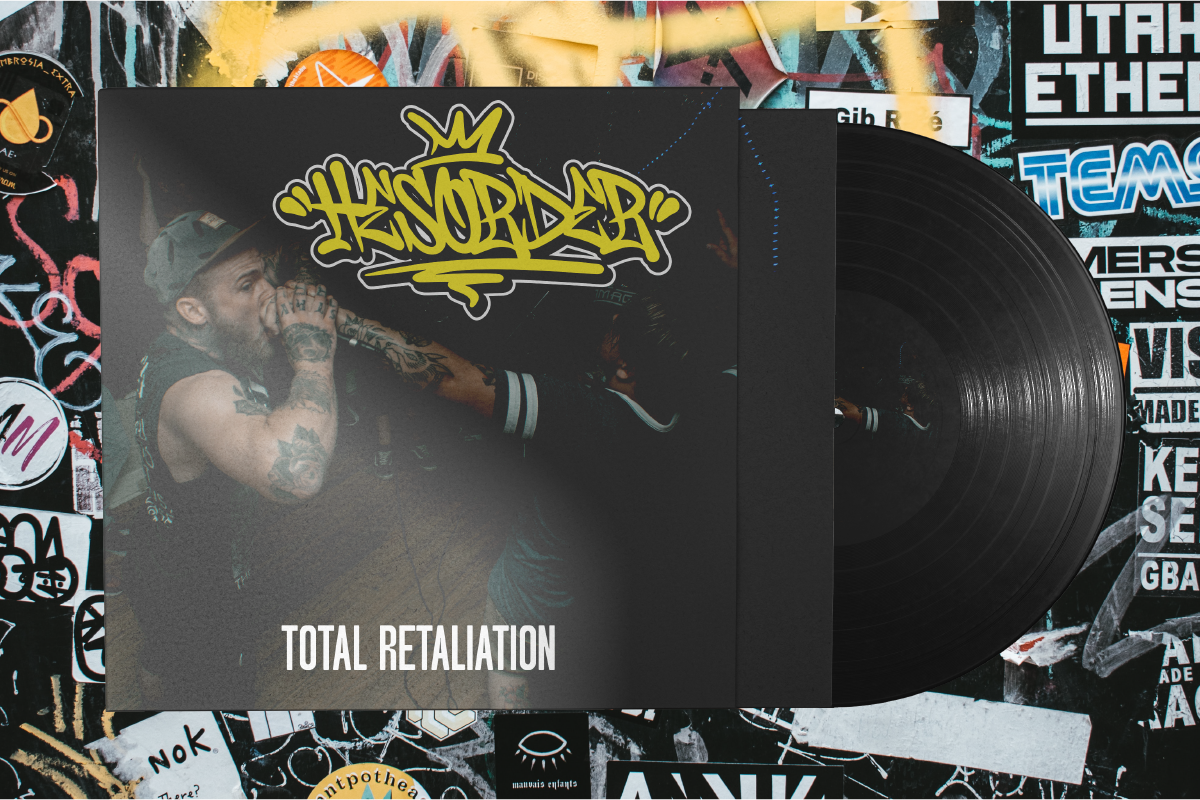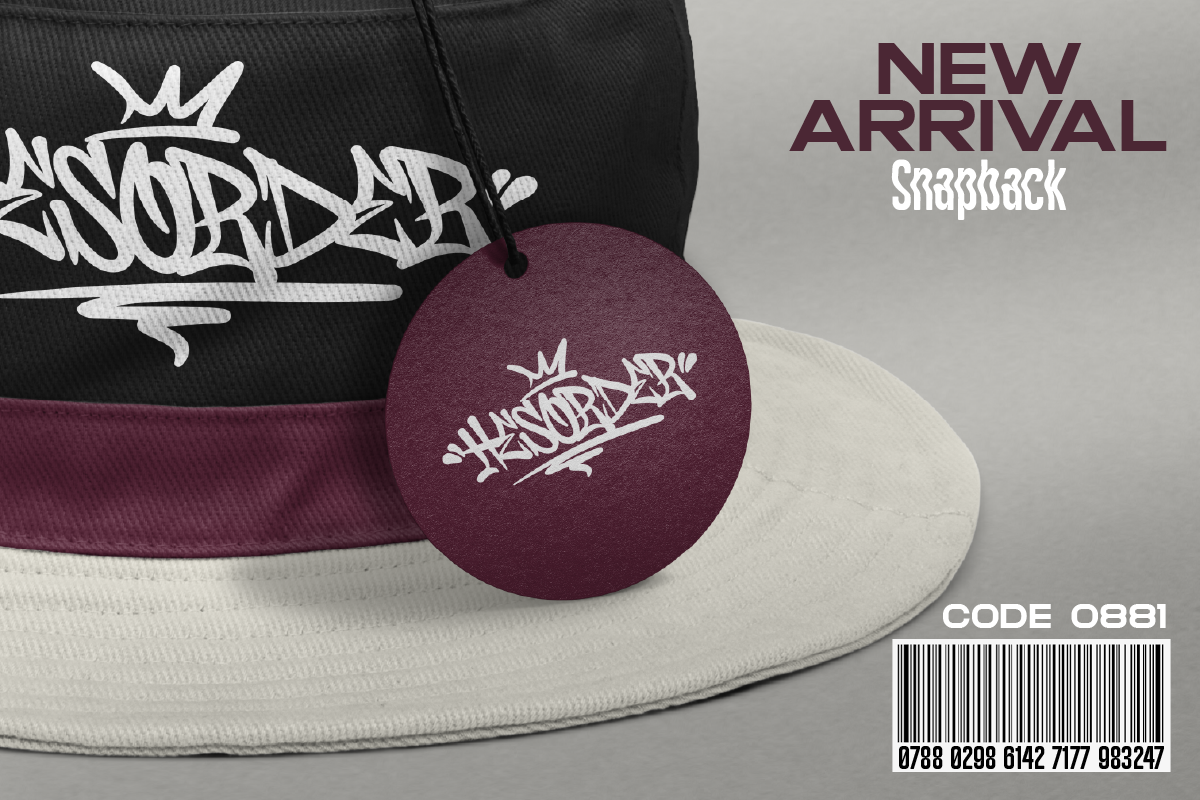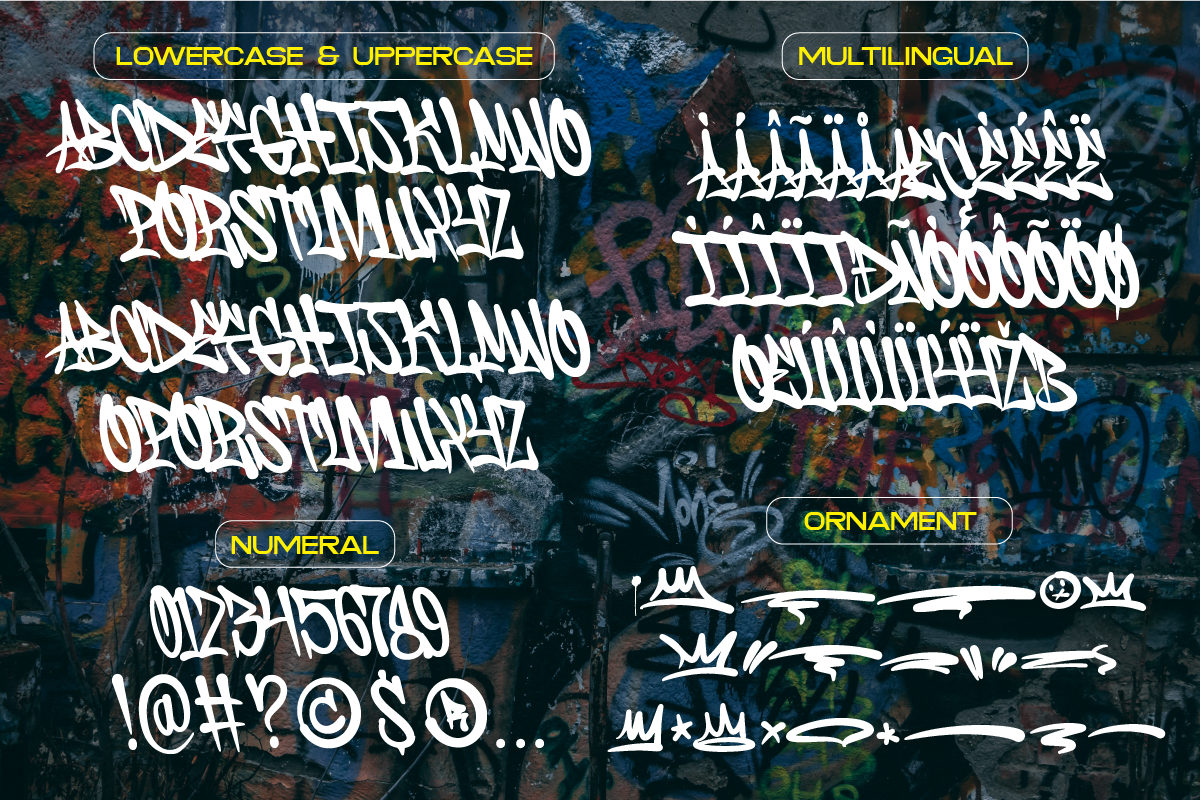
Font Hesorder Terinspirasi oleh gaya marka grafiti jalanan di banyak kota besar. Gaya ini lebih berani dan mudah dibaca, cocok untuk gaya desain "seni jalanan" Anda. Saya menggabungkan pengalaman grafiti nyata ke dalam font komputer, saya pikir akan berbeda dengan font lain jika Anda dapat merasakannya, karena saya menggambar grafiti, menandai, dan memuntahkannya sejak saya masih di sekolah menengah.